Memiliki beragam font sangat diperlukan, terutama kalau Anda bekerja sebagai seorang desainer. Misalnya saja seperti memiliki font Arab untuk membuat desain event tertentu, seperti Idul Fitri, Idul Adha, Maulid Nabi, acara pengajian, dan sebagainya. Sama seperti font pada umumnya, font Arab juga memiliki beragam jenis yang bisa Anda gunakan sesuai kebutuhan.
Mulai dari font Arab jenis brush, pencil, outline dan lainnya. Nah, di sini kami sudah menyediakan beragam jenis font Arab keren yang bisa Anda download dan gunakan gratis. Jadi, Anda bisa pilih salah satu atau beberapa font Arab yang diinginkan. Kalau begitu langsung saja, ini dia kumpulan font Arab keren dan gratis.
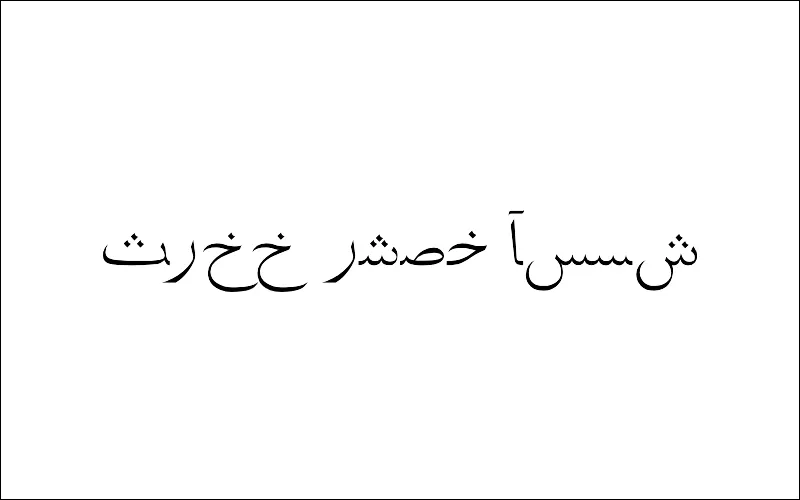
Pertama, Anda bisa download Siddiqua Font. Font Arab yang dibuat oleh Cosmorama ini cukup populer. Di mana memiliki desain sederhana, namun hurufnya sangat lengkap.
Sedang mencari font Arab tanpa fill? Maka Anda bisa menggunakan Max Type Font. Font Arab ini tanpa fill, jadi tampilannya hanya outline saja seperti contoh gambar di atas.
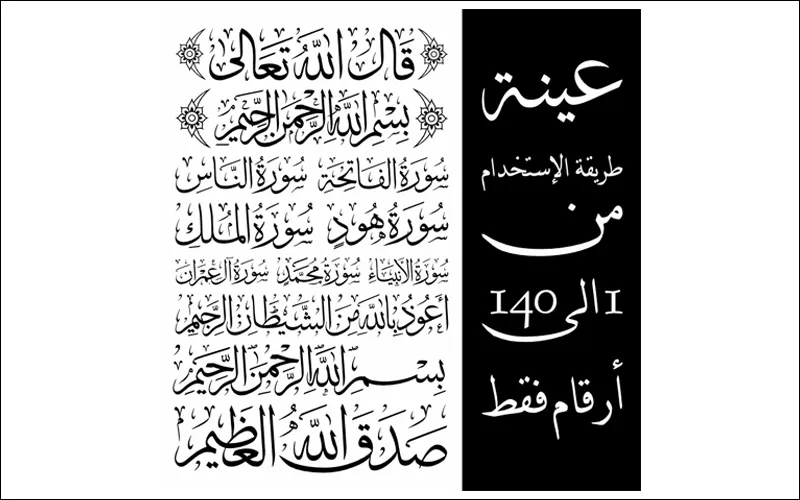
Sesuai dengan namanya, font Arab yang satu ini memiliki bentuk mirip seperti tulisan di Al-Qur’an. Selain itu, di font ini juga terdapat beberapa simbol khusus. Sehingga font Arab ini sering dipakai untuk menuliskan surah atau ayat Al-Qur’an.
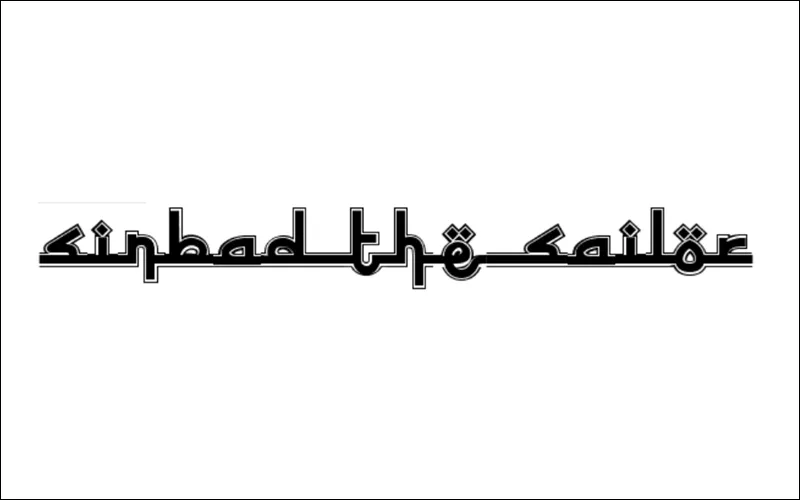
Sinbad the Sailor merupakan font Arab yang sering dipakai untuk membuat judul desain. Karena font ini memiliki karakteristik yang tebal pada fill-nya. Juga terdapat outline putih tebal, sehingga cocok dipilih untuk membuat judul desain islami.
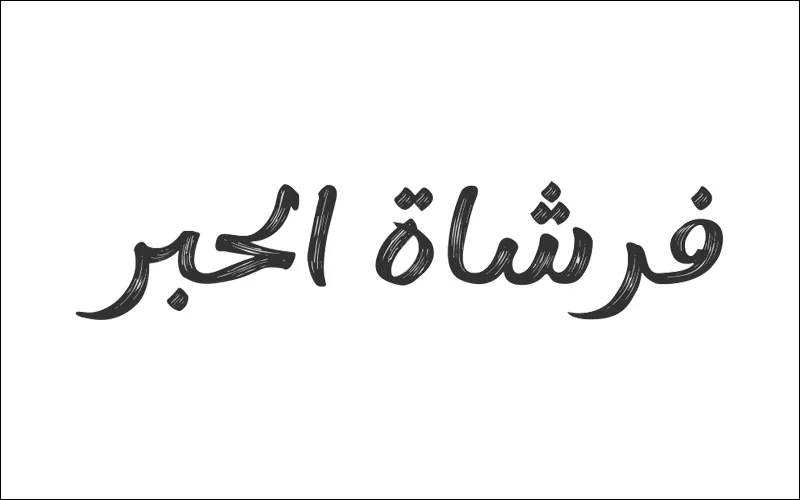
Kemudian ada font Arab Ink Brush Arabic. Sesuai dengan namanya, font Arab ini memiliki bentuk seperti sapuan kuas dengan paduan handwritting yang terlihat menarik. Selain itu, font Ink Brush Arabic ini juga memiliki 462 karakter yang bisa Anda gunakan.
Font Arab menarik lainnya ada Ae Jet. Font ini memiliki karakteristik kaku, sehingga terlihat berbeda dari beberapa font lainnya. Karena ke unikannya, font ini sudah di download lebih dari 3.000 orang.
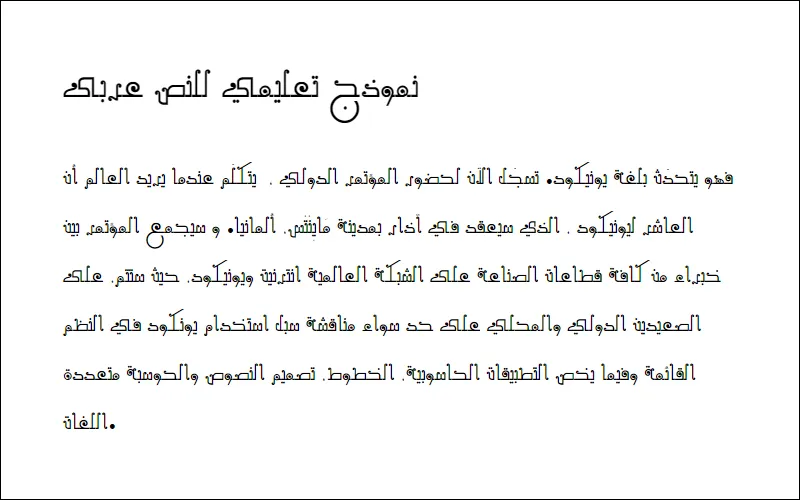
Jika font sebelumnya memiliki karakteristik kaku, maka El Abdaa punya ciri khas berlawanan, yaitu berbentuk melengkung. Ciri khas lainnya dari font El Abdaa ini adalah memiliki titik di setiap karakternya.
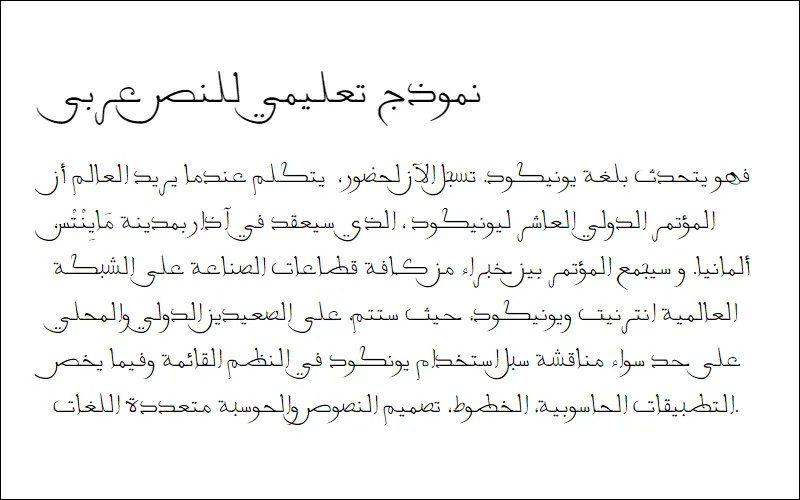
Arabswell 2 cocok digunakan untuk membuat surah atau ayat di desain Anda. Bentuknya yang sederhana dan tipis, membuat font ini direkomendasikan untuk di pilih. Selain itu, Arabswell 2 juga memiliki ciri khas, yaitu coretan di setiap ujung karakter.
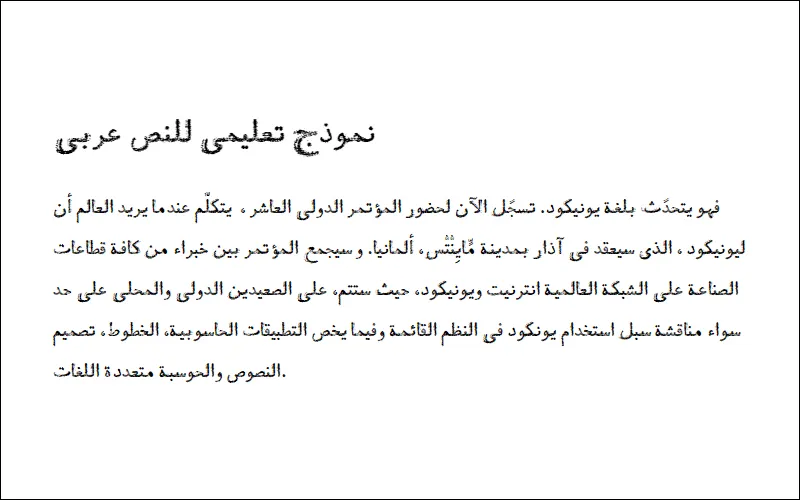
Apabila Anda masih mencari font Arab unik, maka bisa coba pilih A Farhood. Font ini memiliki ciri khas unik juga, yaitu memiliki karakteristik seperti efek glitch.
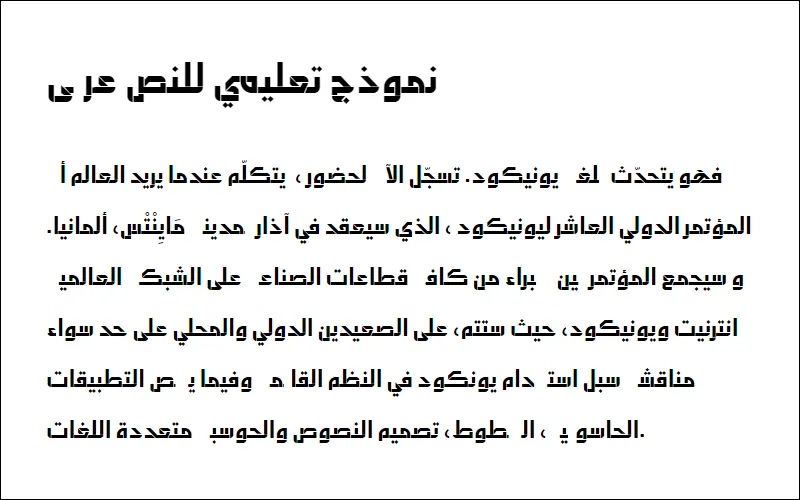
Abdo Salem adalah salah satu font Arab modern. Font ini karakteristiknya tebal, sehingga cocok dipilih untuk membuat judul desain. Selain itu, Abdo Salem memiliki bentuk yang kaku sehingga mirip seperti mesin ketik.
Anda ingin menuliskan surah atau ayat secara lengkap? Jika iya, Anda bisa menggunakan font Arab DecoType Thuluth II. Font ini sederhana, namun terlihat kompleks karena banyak beberapa simbol khusus di setiap karakter.
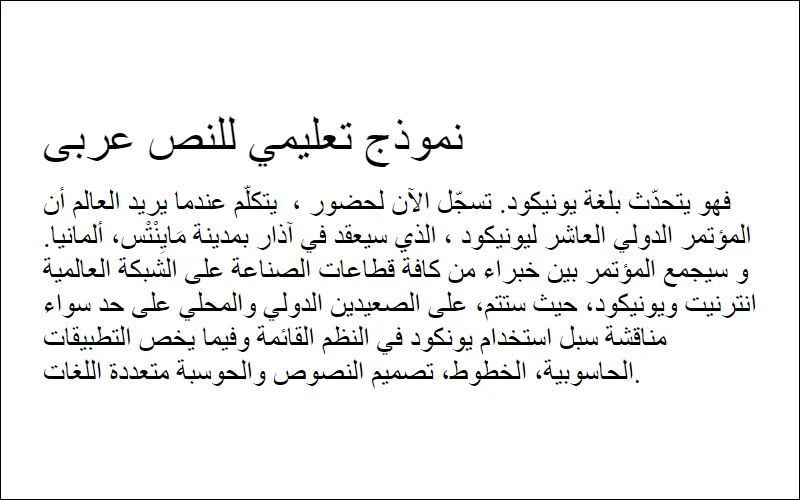
Aga Juhyna Outline merupakan font Arab simpel dengan karakteristik yang cukup tebal. Font Arab ini mirip seperti font yang ada di beberapa buku Islami, seperti Yasin, Do’a, Surah-surah pendek dan lainnya.
Kalau kamu masih mencari font tanpa fill, bisa menggunakan Ae_Shado. Seperti yang Anda lihat, font ini hanya memiliki outline saja. Selain itu, terdapat juga efek shadow di belakang outline tersebut.
AGA Kayrawan Outline adalah salah satu grup font dari AGA Juhyna Outline. Dari segi bentuk, font ini sama-sama memiliki karakteristik yang sederhana dan cukup tebal. Hanya saja, AGA Kayrawan Outline memiliki coretan yang lebih panjang.
Selanjutnya ada font Arab Damavand-Bold. Font ini memiliki bentuk melengkung di setiap sudutnya. Juga seperti namanya, font ini punya karakteristik yang cukup tebal. Jadi kalau Anda ingin membuat judul, bisa menggunakan Damavand-Bold.
Abdo Free merupakan salah satu grup font dari Abdo Salem. Hanya saja, karakteristiknya berbeda. Di mana Abdo Free memiliki format italic dengan desain karakter seperti tulisan tangan.
Mirip seperti Abdo Free, Aldhabi juga menggunakan format italic di setiap karakter-nya. Selain itu, Adlhabi juga punya ciri khas, yaitu tulisan yang tidak lurus, melainkan seperti di tulis dari atas ke bawah.
Sedangkan font Arab ini merupakan satu grup dari font Damavand yang telah kita bahas tadi. Apabila Damavand-Bold sudah tebal, maka Damavand-Heavy punya ketebalan yang lebih tinggi. Jadi, kalau Anda butuh font tebal Damavand-Heavy bisa jadi salah satu solusinya.
Ada beberapa, seperti PakType Naqsh, Mohammed, Syawal Khidmad, Mohammed, Ramadhan Amazing dan Ramadhan Karim.
Font Abdu Salem, Damavand-Heavy, AlHadari, AlHurraTxtBold, B Elham, B Esfehan, B Jadid Bold dan font tebal lainnya.
Anda bisa gunakan font Mukadimah, Syawal Khidmat atau Mohammed.